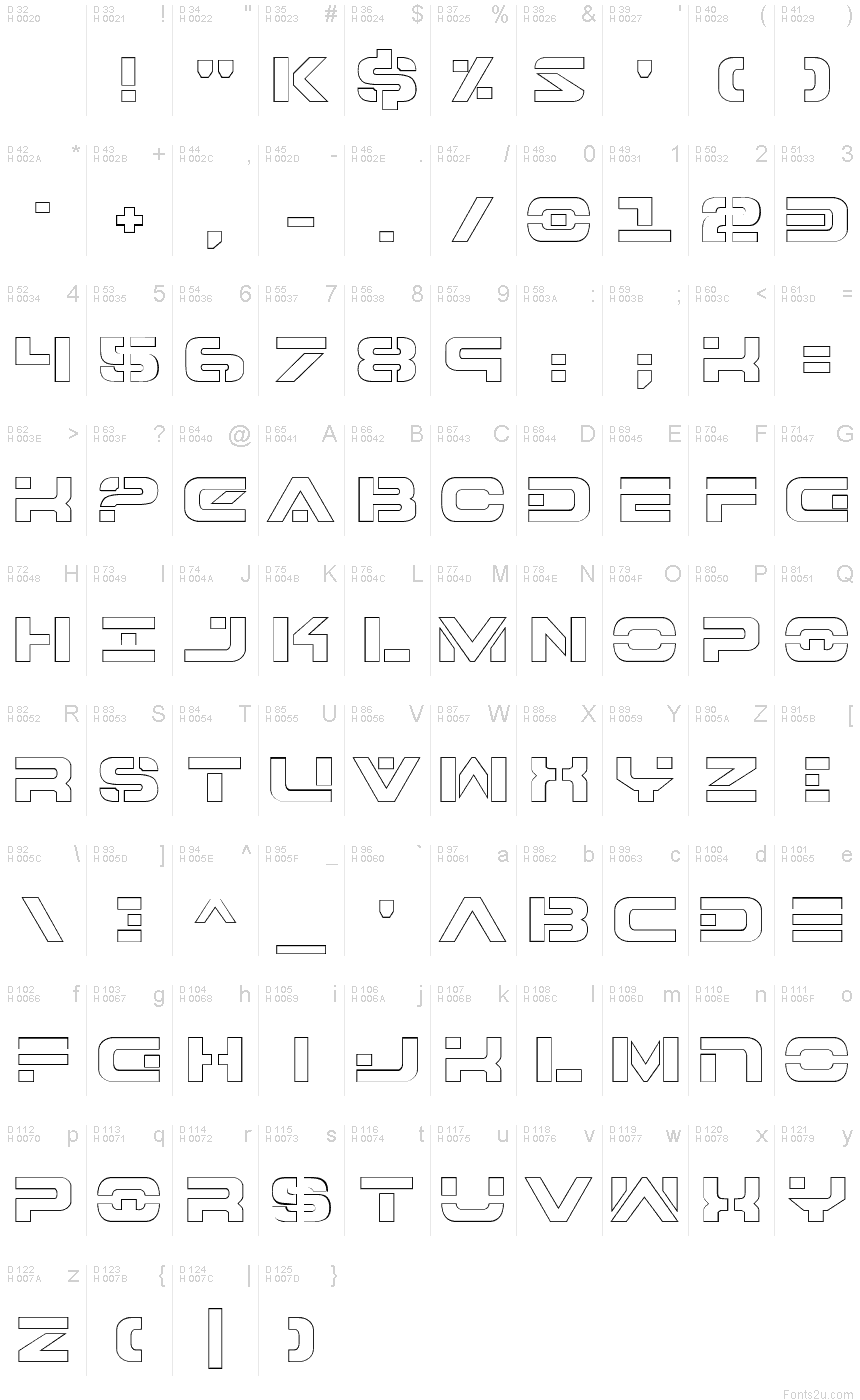
"7th Service" ist eine markante, futuristische Schrift, die eine militärisch inspirierte Ästhetik ausstrahlt. Entworfen von Iconian Fonts, zeichnet sich diese Display-Schrift durch ihren kräftigen, umrandeten Stil aus, der sofort ins Auge fällt.
Die scharfen, kantigen Buchstabenformen und präzisen Kanten vermitteln ein Gefühl von Stärke und Exaktheit. Damit eignet sich die Schrift hervorragend für diverse Designanwendungen – von Branding und Verpackungen bis hin zu redaktionellen Layouts und digitalen Interfaces. Ihr einzigartiger Charakter ist ideal für Projekte, die einen robusten, ausdrucksstarken Look erfordern, etwa bei Produktdesigns, Event-Promos oder Videospiel-Logos.
Insgesamt ist "7th Service" eine vielseitige und visuell überzeugende Schrift, die jedem Projekt das gewisse Extra verleiht.
7th Service Outline